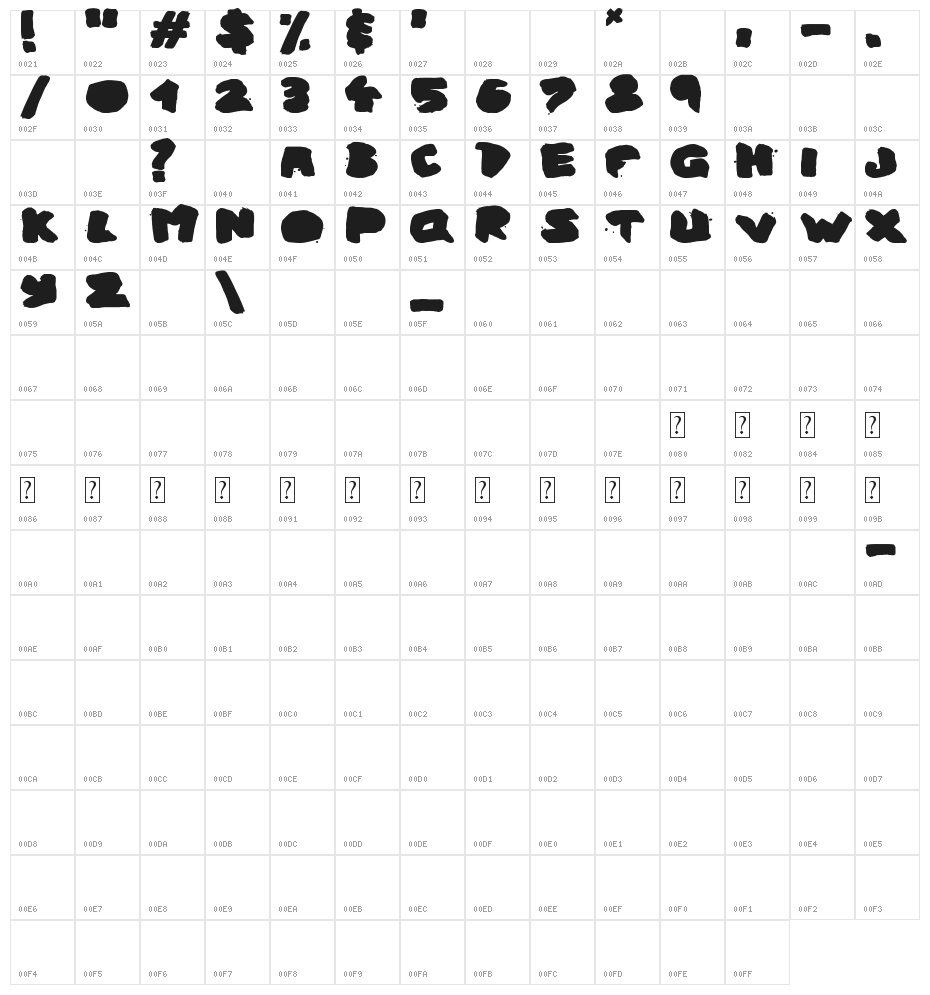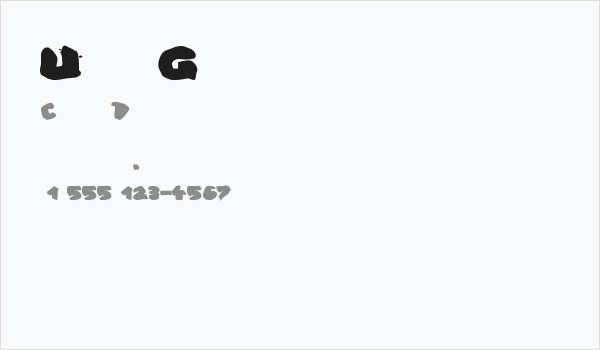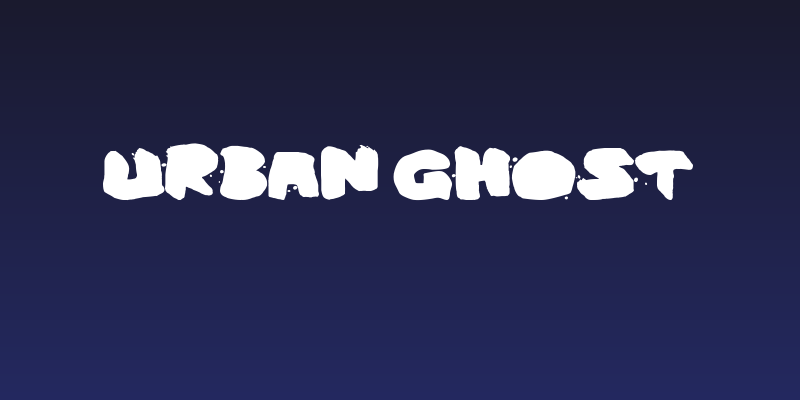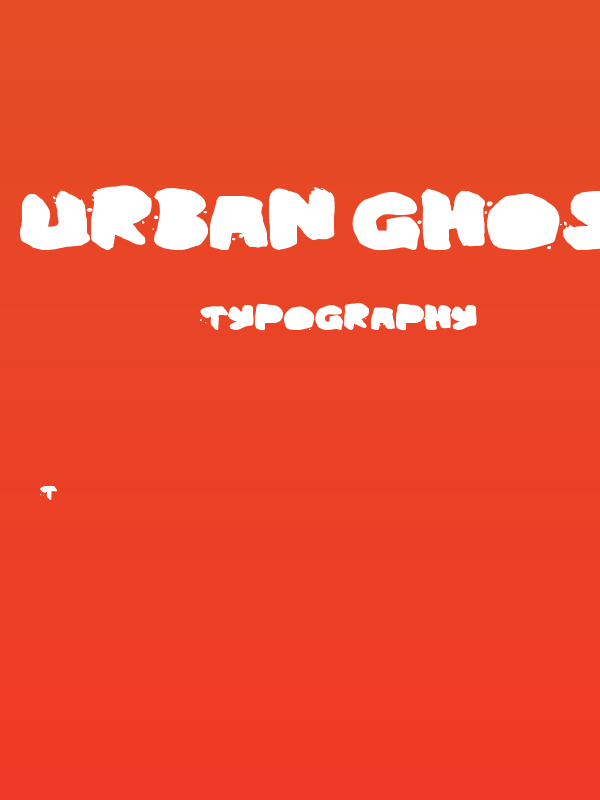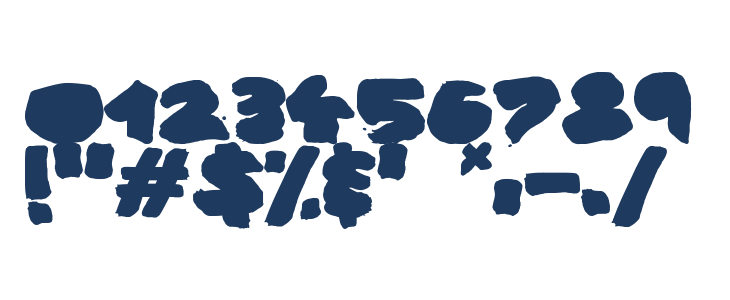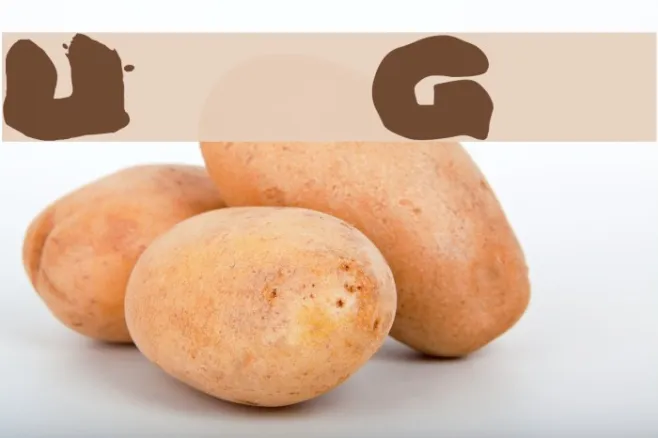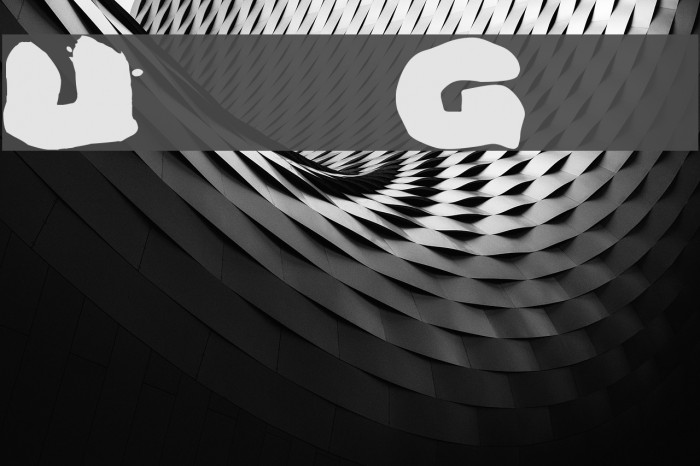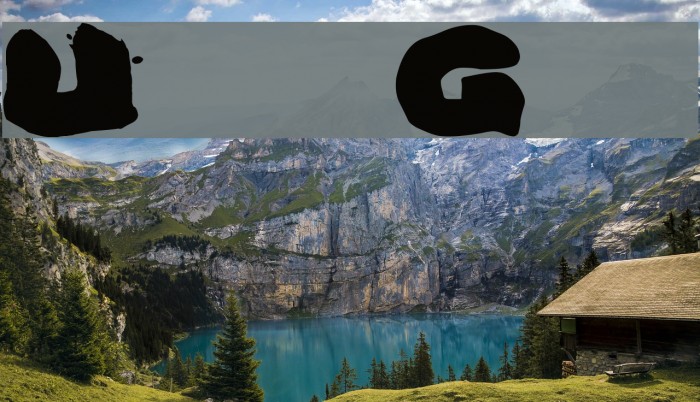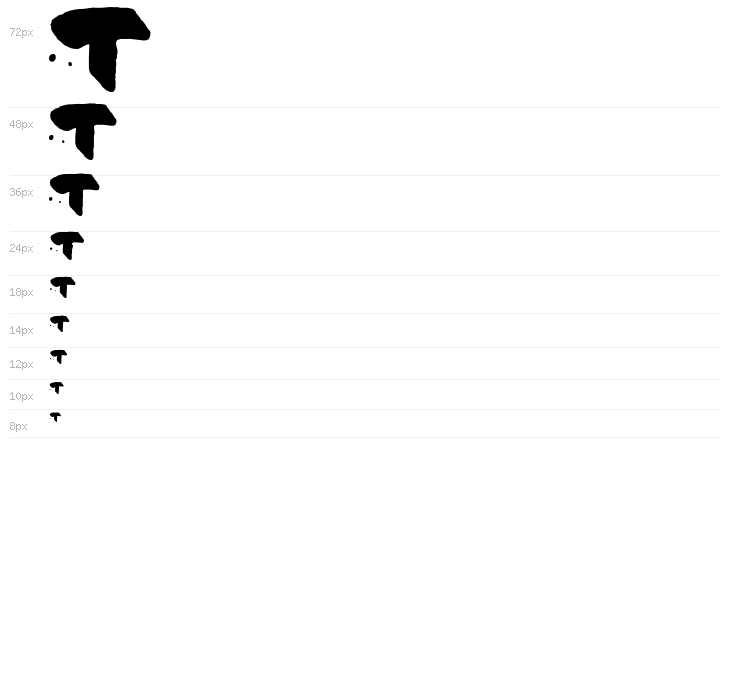
Urban Ghost Font
| Estilo general | Urban, Graffiti, Bold |
| Caso de uso | Logos, Posters, Headlines |
| Proyectos propuestos | Ideal for street art-themed designs, music album covers, posters, and branding that requires a bold, edgy look. |